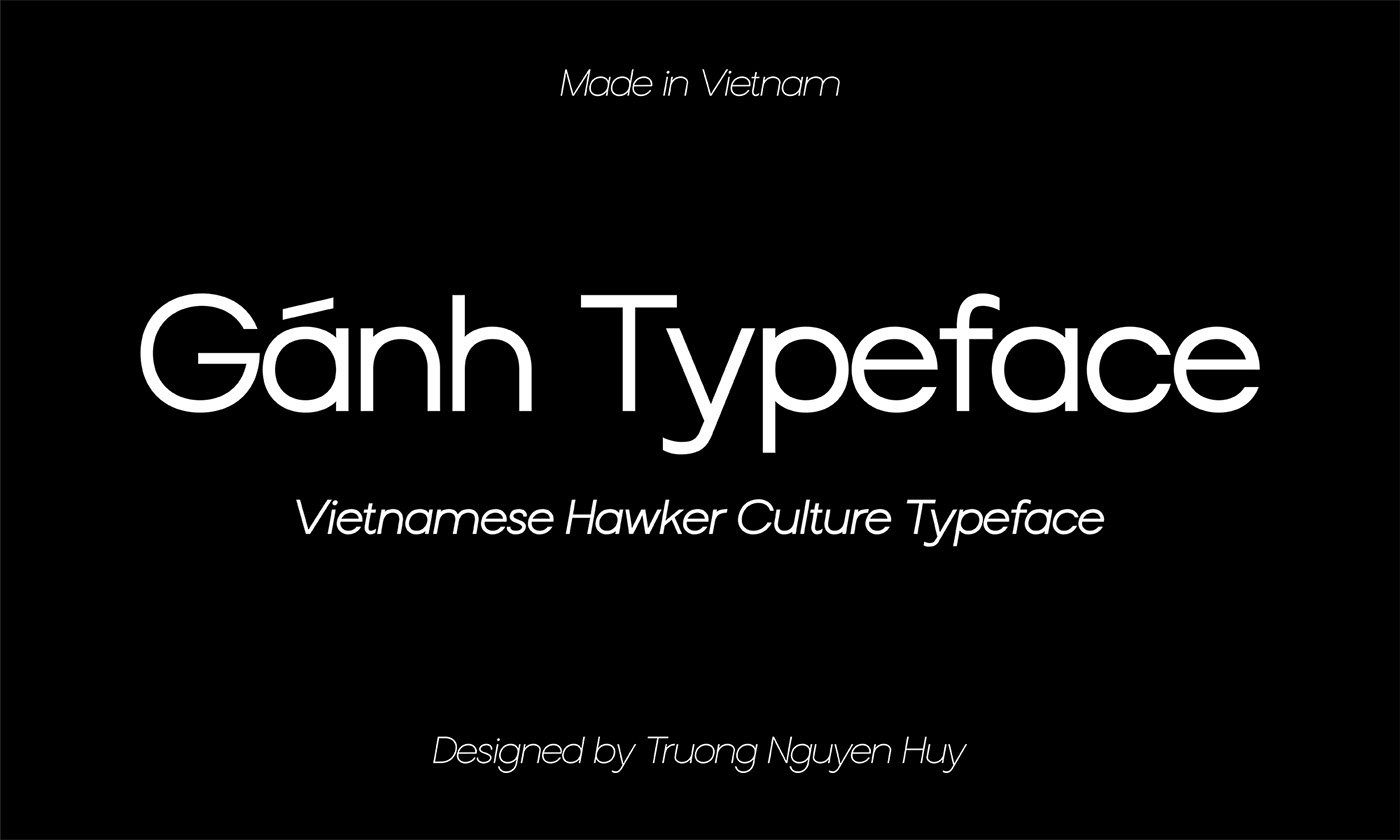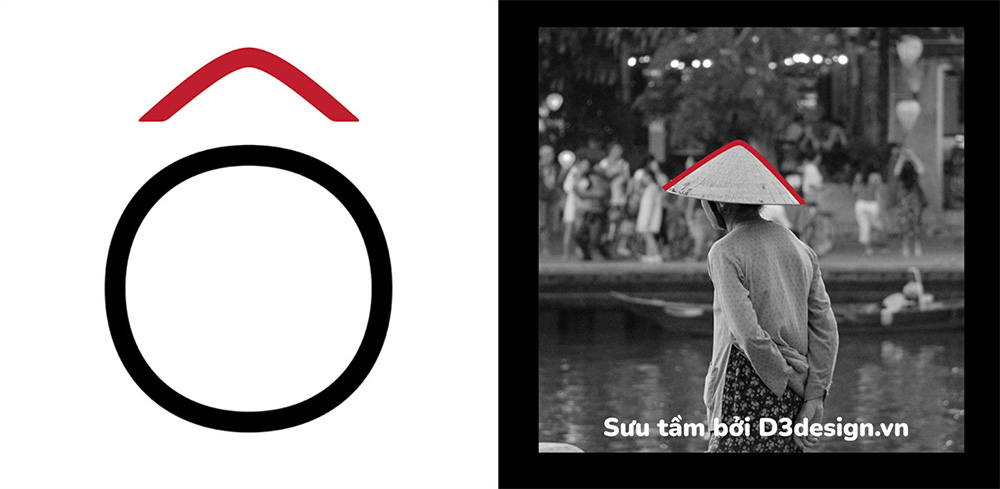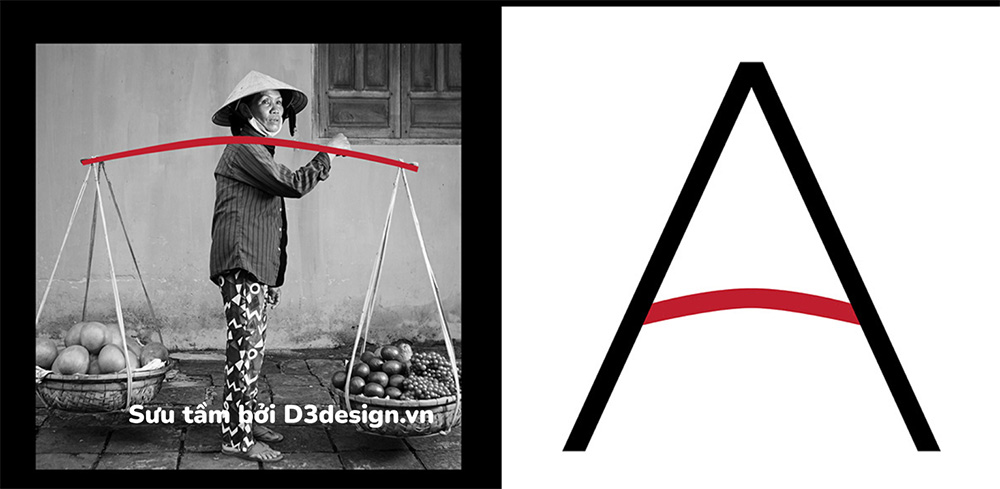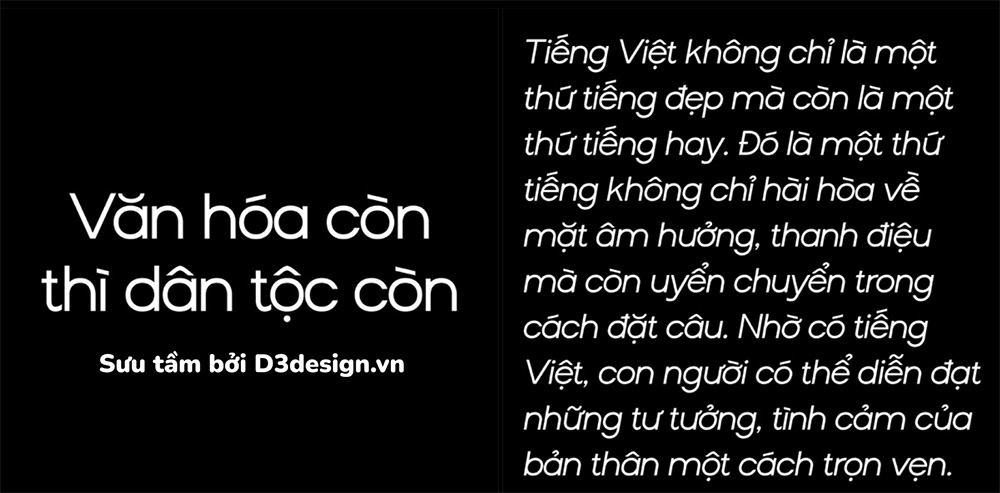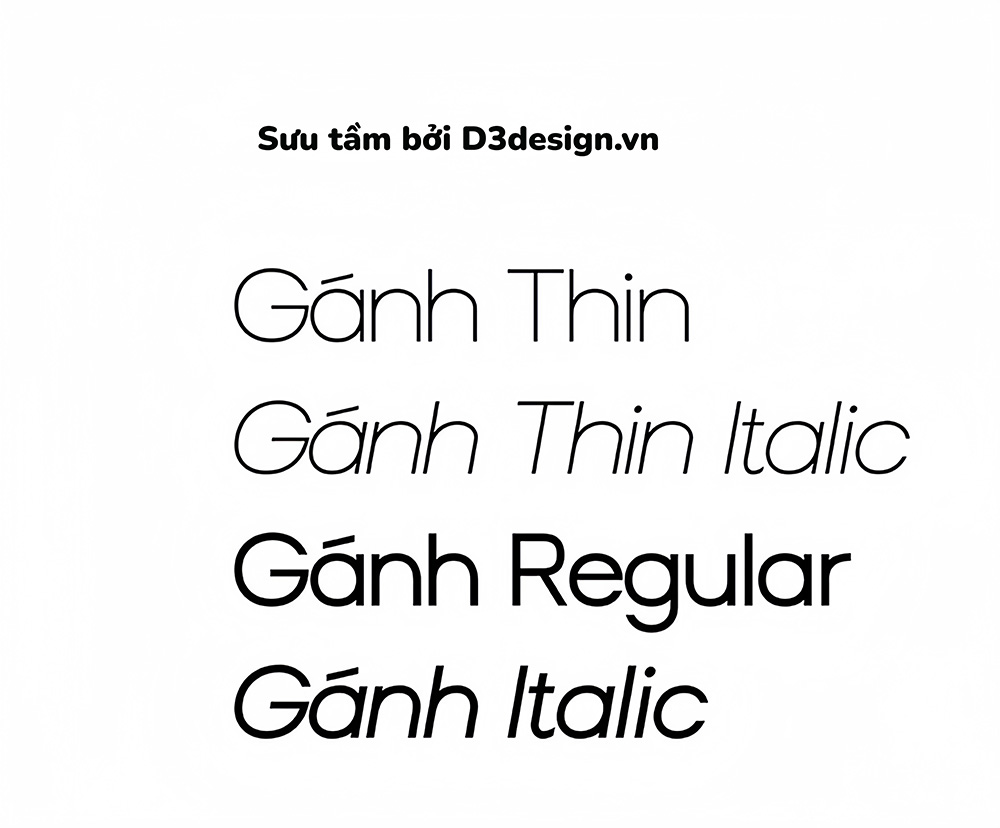
Font Chữ Tiếng Việt "Gánh" Mang Nét Văn Hóa Của Người Việt Nam
Gánh hàng rong là một trong những nét văn hóa của người Việt Nam. Những người phụ nữ với đôi quang gánh trên vai, bươn chải trên từng con phố. Gánh hàng rong không chỉ là một phương tiện mưu sinh mà còn là biểu tượng của sự kiên nhẫn, chịu thương chịu khó và tình yêu thương gia đình. Hình ảnh ấy đã trở thành một phần không thể thiếu trong đời sống người dân Việt Nam.
Kiểu chữ “Gánh" được thiết kế dựa trên những nét đặc trưng từ hình ảnh người bán hàng rong ở Việt Nam. Bên cạnh đó hình dáng của kiểu chữ được phát triển từ hình tròn, với chiều cao x-height lớn giúp trải nghiệm đọc thoải mái.
Tên font: Gánh Typeface
Tác giả: Truong Nguyen Huy